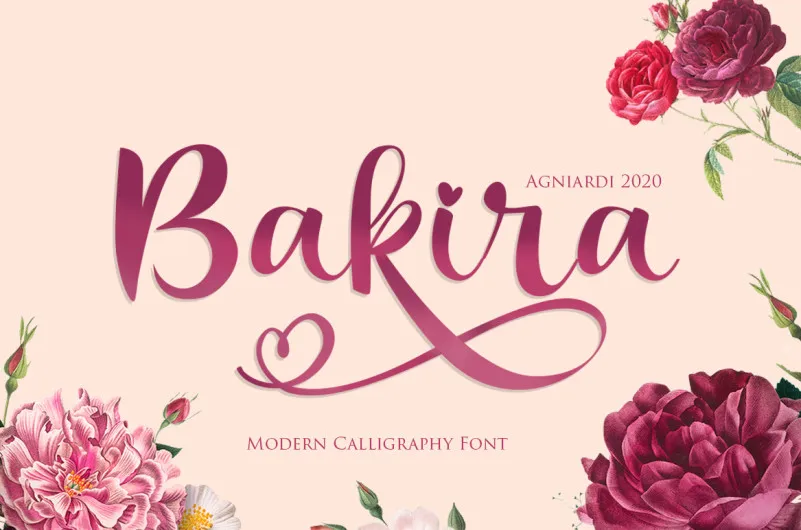
Bakira – Modern Calligraphy Font – Download Grátis
A Bakira é uma fonte tipográfica moderna com um estilo script único e elegante, desenvolvida para projetos que precisam de um toque sofisticado e refinado. Seu design fluido, quase como uma escrita manuscrita, combina perfeitamente para criar identidades visuais de marca em alta qualidade, designs de móveis de uso doméstico, embalagens de produtos, até mesmo para personalizar cartões de nome e convites. Com um total de 215 símbolos, a Bakira se ajusta perfeitamente ao seu design digital, oferecendo uma abordagem moderna às antigas técnicas de escrita filigranada. Perfeito tanto para o texto como um fundo decorativo, ela é uma escolha excepcional para qualquer projeto que busque trazer elegância a qualquer layout ou imagem de fundo.